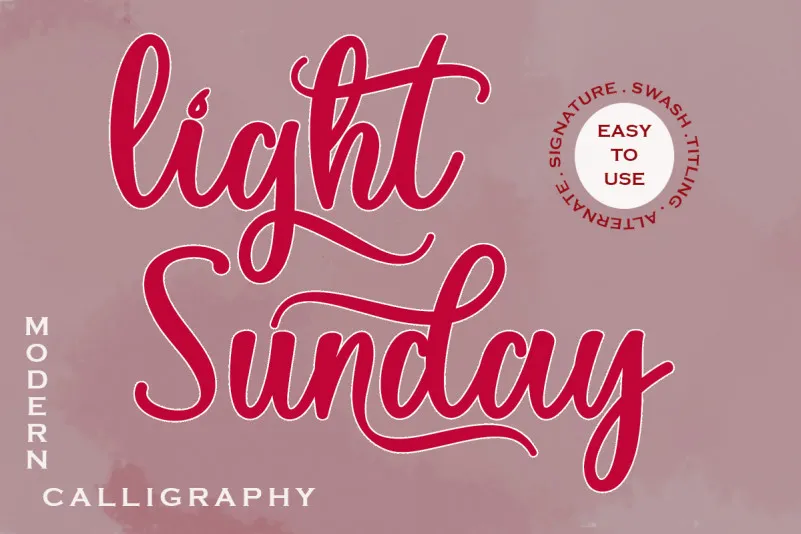
Na elegante Light Sunday Font Script, você encontra uma tipografia fluida e versátil que é perfeita para criar mensagens agradáveis e profissionais. Esta fonte, criada pelo talentoso Designer Yoga Letter, incorpora um toque de delicadeza e modernidade em cada caractere. Com seu estilo suave e natural, a Light Sunday Font é ideal para uso em design editorial, websites pessoais ou qualquer projeto que deseje transmitir uma mensagem amigável e autêntica. Seja você criando designs para redes sociais, sites de comunicação ou até mesmo impressões digitais, esta fonte trará um toque único e alegre a seu trabalho. Agora que você tem acesso à essa poderosa fonte, o que mais vai fazer parte do seu arsenal? Experimente e descubra como Light Sunday Font Script pode transformar seus projetos em verdadeiras obras de arte digitais.